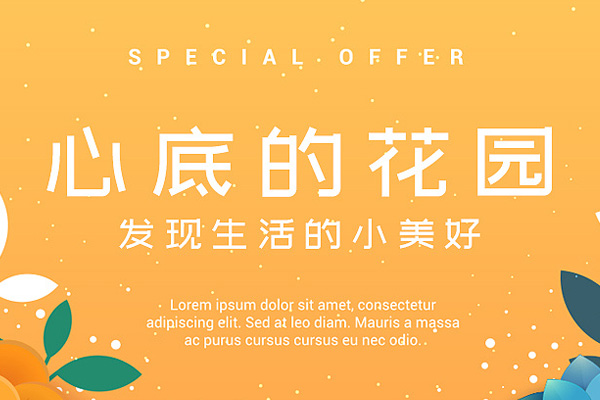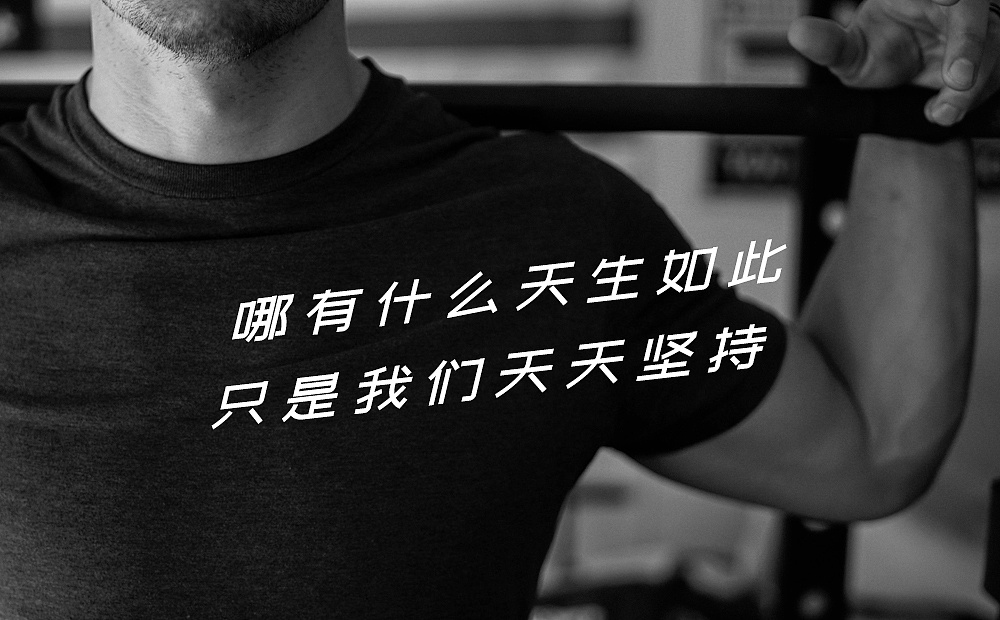
站酷文艺体
站酷文艺体是由知名字体设计师刘兵克负责字形和规范,并由刘兵克工作室以及字体设计直播课学员共同创作完成的。这款字体的字形设计新颖独特,简洁而不失力度,色彩清新淡雅,文艺范儿十足。它包含了7155个常用汉字、52个英文字母、10个阿拉伯数字以及67个常用标点符号,实用性非常高。郑庆科设计师最后完成了字库的生成工作。站酷文艺体的出现,让我们看到了传统书写艺术与现代科技的完美结合。
站酷文艺体效果预览
站酷文艺体字体效果预览